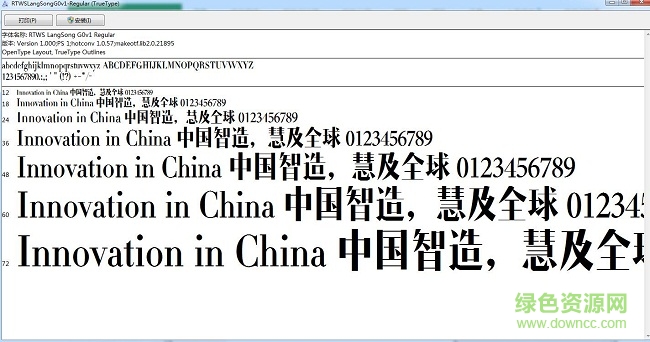
rtwslangsongg0v1 regular字體
造字工房朗宋g0v1常規(guī)體(rtwslangsongg0v1 regular)是一款端莊美觀的宋體字體,字形舒展,筆畫挺勁,雅致耐看,印刷效果好,閱讀體驗(yàn)舒適,需要的小伙伴快來下載吧!
宋體起源介紹
宋體字是源于宋代的,但是宋體字在明代確立,所以至今在日本,宋體字仍被稱作“明朝體”。宋體字是印刷行業(yè)應(yīng)用得最為廣泛的一種字體,根據(jù)字的外形的不同,又分為書宋和報宋。
宋體特點(diǎn)
中國書法和雕版印刷的結(jié)合產(chǎn)生了宋體字,因此,宋體字不但有中國書法的魅力,還具有雕版印刷及木版刀刻的韻味。